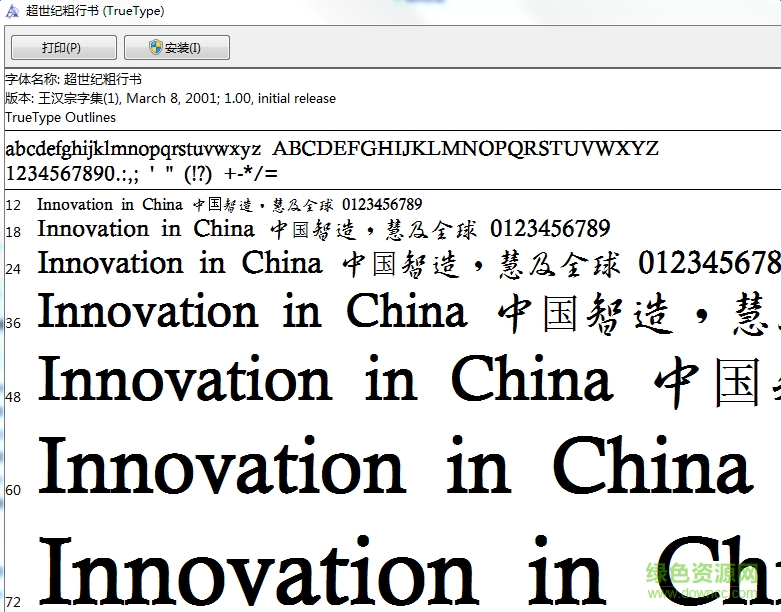
超世紀粗行書字體是一款超世紀粗行書,含繁體和簡體兩種字體哦,美觀又大方,字體在生活中還是比較常見的,能夠在海報和電影電視之中經(jīng)常的看到這樣的字體,全方位滿足用戶的需求,喜歡就來下載體驗唄!
超世紀粗行書是一款應用于設計方面的中文簡體字體,外形漂亮大方,字形瀟灑,可以應用于藝術(shù)設計、產(chǎn)品包裝、平面廣告等行業(yè)領域,喜歡的用戶可下載收藏。